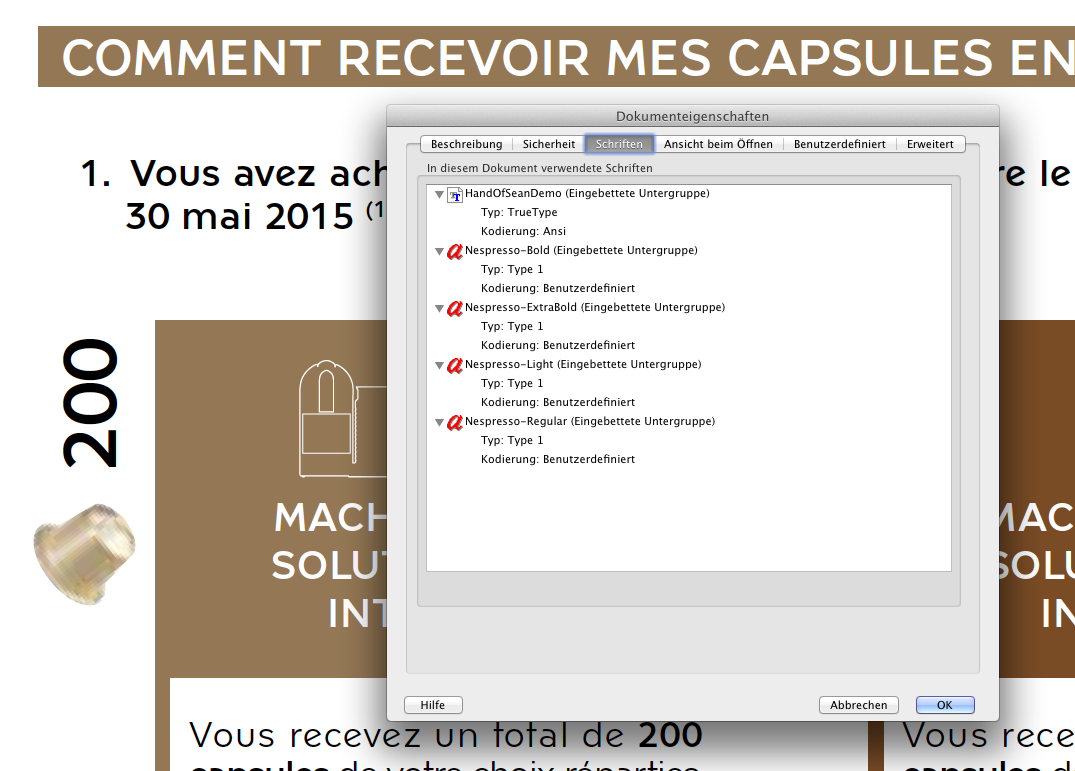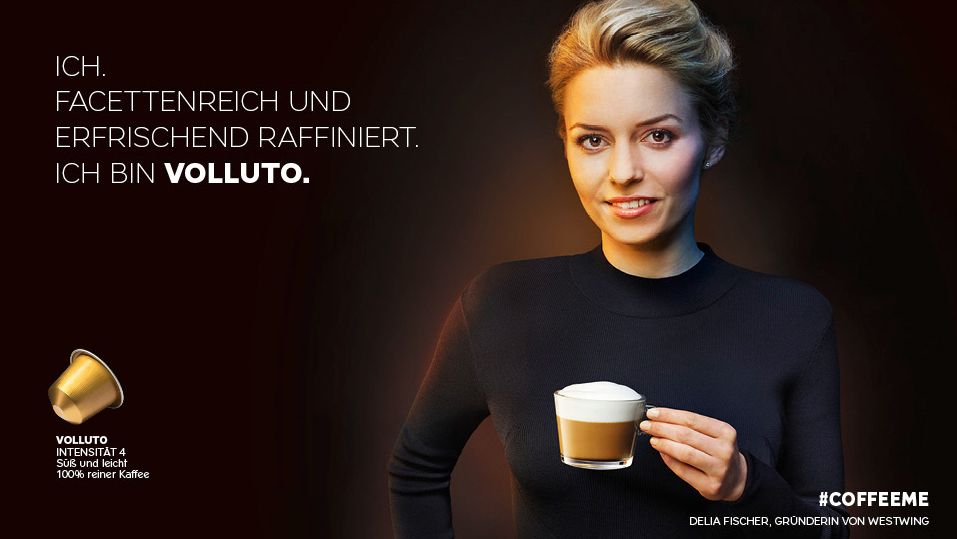
ich suche den font von einem "Nespresso-Volluto"- Plakat, eine aktuelle Kampagne. Wäre prima, wenn ihr mir helfen könntet, über WhatTheFont habe ich leider nichts gefunden.
Puh, das dürfte schwierig werden. Die gezeigten Buchstaben sind allesamt nicht sehr gut geeignet, eine Schrift eindeutig zu identifizieren, weil sie keine besonders markanten Formen beinhalten, lediglich Kreisformen und Geraden. G, R, W oder auch Kleinbuchstaben wären da größere Hilfen. Du hast nicht zufällig weitere oder größere Schriftbeispiele dieser Schrift vorliegen?
Rein vom Gefühl her würde ich mir an Deiner Stelle mal geometrisch konstruierte Schriften vornehmen wie die Futura oder die Gotham und einen Vergleich anstellen.
Leider habe ich online nur das anhängende Bild und auch nichts größeres gefunden, die Schrift scheint nur für die Plakate genommen zu werden. Die Futura Bold sieht aber ja schon mal ganz gut aus, Danke.
Na ja, aber auf dem Plakat sind doch zumindest deutlich mehr Buchstaben der Schrift drauf, die die Identifikation viel leichter machen! Ist zwar ein feinerer Schnitt, aber das macht ja nichts. Der feine Schnitt sagt jedenfalls, dass es sich nicht um die Futura handelt. Ich würde an Deiner Stelle mal mein Augenmerk auf den Buchstaben R legen bei der Suche und auch das M ist markant.
Das ß könnte übrigens auch helfen. Welche Schriften sind das denn noch, die so tief ansetzen? Da gibt es doch eigentlich gar nicht so viele …
Die Nespresso-Volluto-PDFs, die im Internet zu finden sind, verwenden Frutiger, das hilft uns auch nicht weiter.  :-?
Sehr nah an Dalton Maags Effra:
Das R ist anders, aber das R sieht auch so aus als hätte man es modifiziert ... was sich Nestle ja leisten kann, selbst bei Dalton Maag.
Kommt mir irgendwei vertraut vor?! Neutra Text Irgendwas? Neutra Irgendwas Text? Diese da?
Neutra 2 Text
Designers: Richard Neutra and Christian Schwartz
Year: 2002
Publisher: House Industries
Das ist aber nicht die Schrift, die bei VOLLUTO verwendet wurde. Das O ist beim gesuchten Schriftzug rund und beim Nespresso-Font nicht … ?